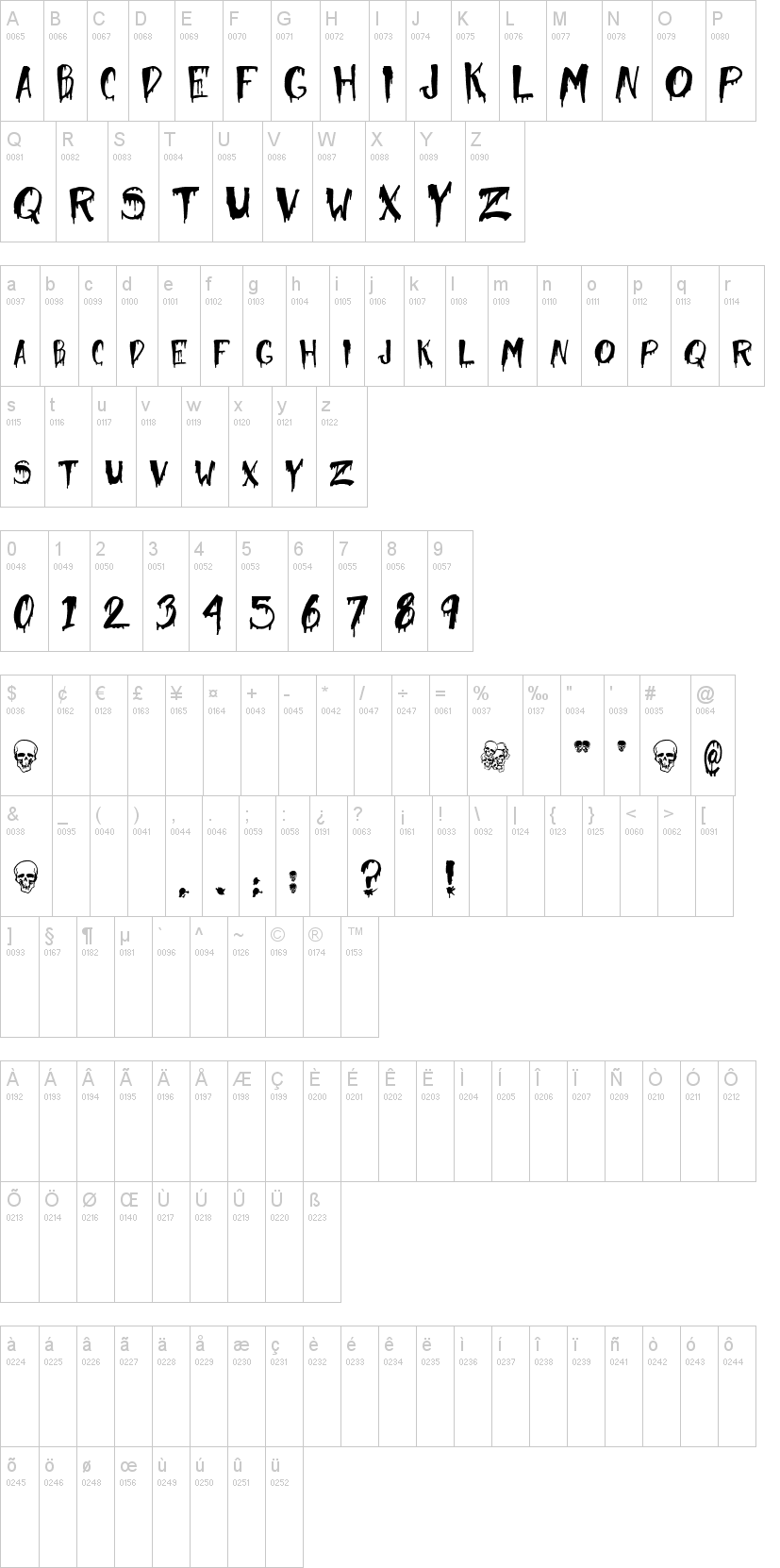
Halloween Too是一种免费的万圣节字体,它的设计灵感来自于传统的万圣节元素,如蝙蝠、南瓜、骷髅头等。这种字体的主要特点是其不规则的线条和锯齿状的笔画,这些特点给人一种神秘、诡异的感觉,非常适合用于万圣节相关的文本设计和装饰。Halloween Too字体包含大写字母、小写字母、数字和标点符号等基本字符,支持英语和西欧语言。如果你正在寻找一种能够增强万圣节气氛的字体,那么Halloween Too将是一个非常好的选择。内容介绍
Halloween Too是一款非常不错的手写艺术字体,具有很好的视觉感,适合于文化类的宣传设计、商业类品牌的广告和产品包装设计以及个性化文字排版等较多场景。